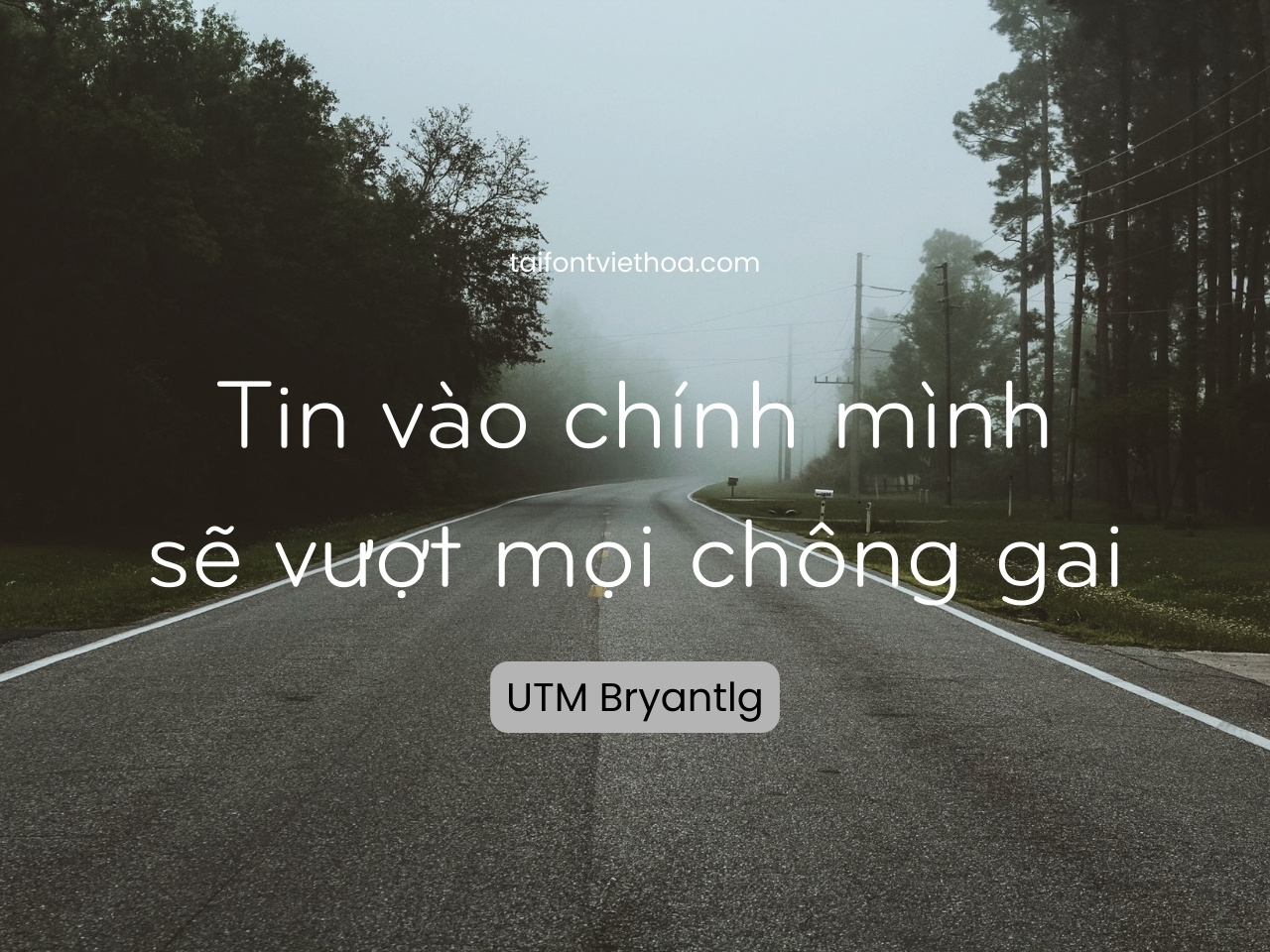
Font việt hóa UTM Bryantlg đầy đủ
Giới thiệu về font UTM Bryantlg Trọn Bộ
UTM Bryantlg Trọn Bộ là phiên bản Việt hóa của bộ font Bryantlg – một bộ font sans-serif hiện đại, mạnh mẽ và linh hoạt, được thiết kế dành cho các dự án thiết kế đa dạng. Bộ font nổi bật với các nét chữ gọn gàng, vuông vức và cân đối, mang lại sự chuyên nghiệp và hiệu quả trong truyền tải thông điệp. Phiên bản Việt hóa đã được hoàn thiện để hỗ trợ đầy đủ tiếng Việt cùng hơn 200 ngôn ngữ khác, giúp mở rộng khả năng sử dụng trong cộng đồng thiết kế Việt Nam và quốc tế.
Bộ font UTM Bryantlg được taifontviethoa.com sưu tầm và chọn lọc kỹ càng nhằm đáp ứng nhu cầu đa dạng của giới thiết kế. Phiên bản Việt hóa đảm bảo khả năng hiển thị tiếng Việt sắc nét, phù hợp với nhiều phong cách thiết kế từ thương hiệu đến quảng cáo và truyền thông số.
Đặc điểm thiết kế và ứng dụng của UTM Bryantlg Trọn Bộ
UTM Bryantlg sở hữu cấu trúc sans-serif không chân, với các nét chữ vuông vức, đồng đều và rõ ràng. Bộ font có nhiều trọng lượng và biến thể, cho phép các nhà thiết kế linh hoạt sử dụng trong nhiều bối cảnh từ tiêu đề nổi bật đến nội dung chi tiết. Thiết kế font đơn giản, hiện đại và dễ đọc, phù hợp với nhiều loại hình thiết kế và truyền thông.
Bộ font thích hợp sử dụng trong thiết kế website, nhận diện thương hiệu, bao bì sản phẩm, brochure, poster và các dự án truyền thông đa phương tiện. Các ngành nghề phù hợp bao gồm: công nghệ, truyền thông, giáo dục, startup và thương mại điện tử.